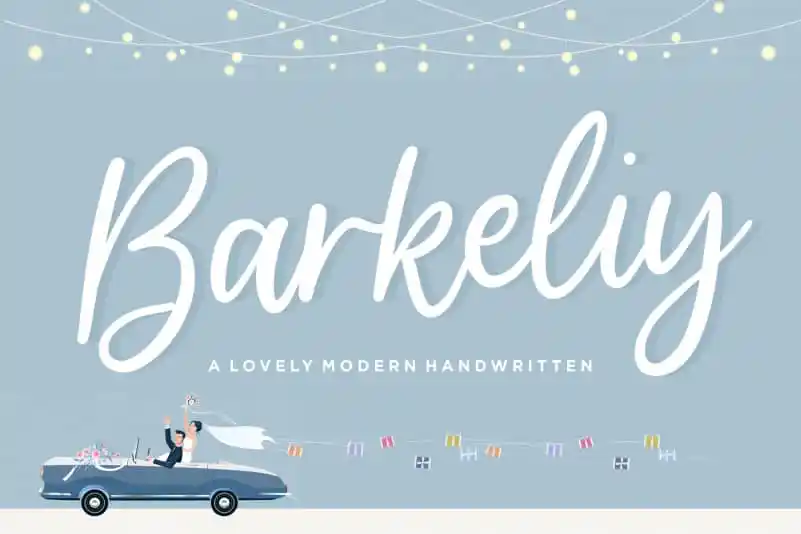
A fonte ‘Barkeliy Lovely Handwritten Font’ é perfeitamente adaptada para projetos visuais criativos e vibrantes. Seu ar macio e encantador permite que sua linguagem seja expressa de maneiras não tão diretas, permitindo um toque delicado em qualquer projeto que ela se encaixa. Especialmente adequada para aplicativos como embalagens de produtos, identidade visual, revistas, mídia social ou até mesmo para dar um toque especial a mensagens importantes. Suas linhas fluidas e o ar de amizade que transmitem são perfeitos para qualquer ocasião especial ou ambiente casual. A fonte é uma escolha ótima para quem busca algo mais suave e aconchegante, sem perder sua essência criativa. Seja você um designer gráfico em constante criação, um editor de fotos com um novo projeto que precisa de um toque personalizado ou mesmo alguém usando o design para expressar sentimentos pessoais, ‘Barkeliy Lovely Handwritten Font’ é uma fonte perfeita para ajudá-lo a dar vida à sua ideia.